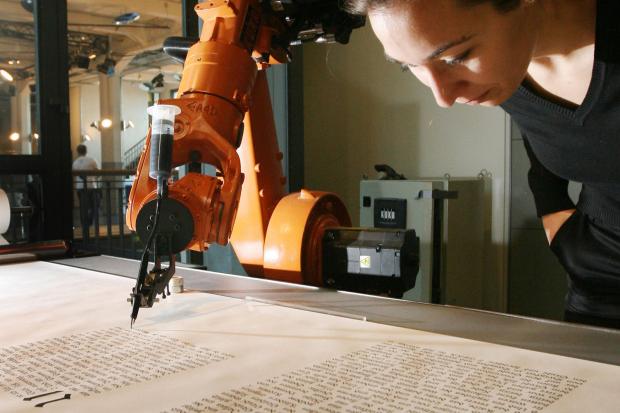
1 Liter Tinte und 1 Kilometer Papier: Die Bibel wurde abgeschrieben.
Ach wie schön, dass der Roboter nicht nur ‘Kalligraphische Linen’ sondern auch gleich Blocksatz geschrieben hat. Ob die Silbentrennung eingeschaltet war? Aber es ist ja Kunst, nicht wahr?